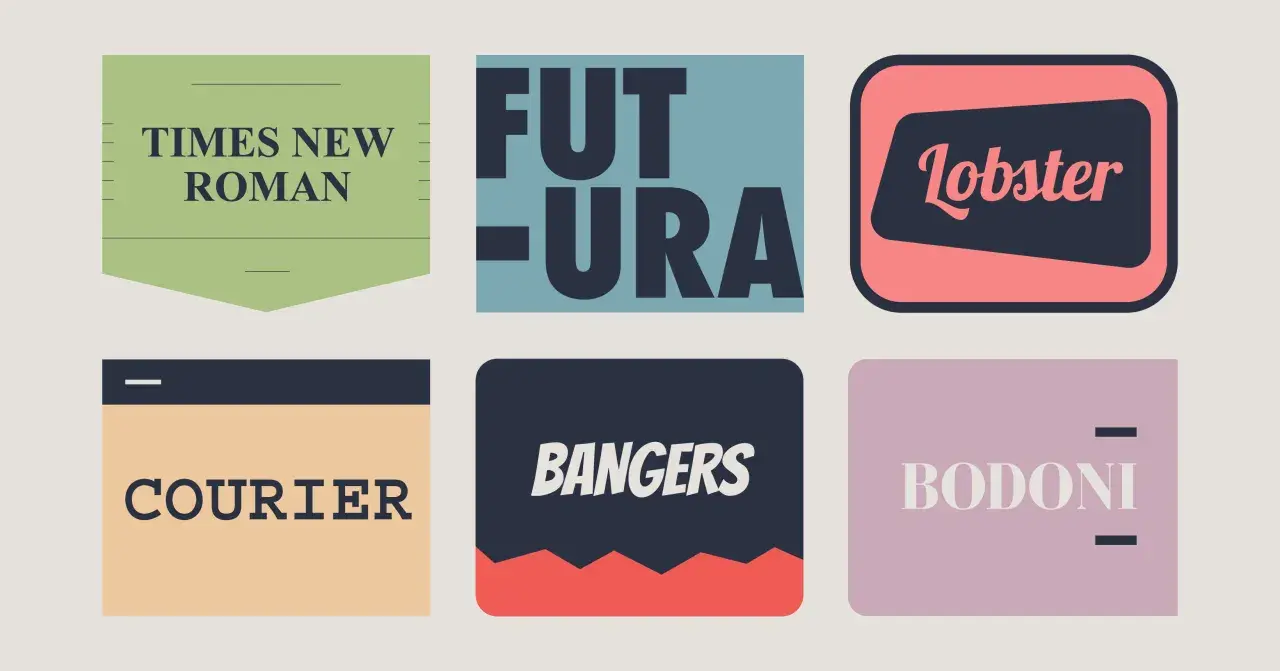
Dobór kroju pisma ma dziś większy wpływ na odbiór marki niż wielu właścicieli firm zakłada. Gdy analizuję popularne czcionki, patrzę nie tylko na modę, ale przede wszystkim na czytelność, charakter i to, czy dana rodzina rzeczywiście pomaga sprzedać usługę lub produkt. W tym tekście pokazuję, które kroje są najczęściej wybierane, dlaczego właśnie one wracają w projektach oraz jak dobrać font do strony, reklamy i materiałów lokalnego biznesu.
Najmocniejsze kroje to dziś te, które łączą czytelność z charakterem
- W interfejsach i na stronach nadal dominują proste sans-serify, bo są najłatwiejsze do czytania na ekranie.
- Inter, Roboto, Open Sans, Lato, Montserrat i Poppins to nazwiska, które wracają najczęściej, ale każdy z tych krojów ma inne zastosowanie.
- Serify znów zyskują znaczenie w markach premium, edytorialu i treściach eksperckich, bo dodają więcej powagi i ciepła.
- W praktyce lepiej wybrać 1 lub 2 rodziny pisma niż gonić za kolejną modną nazwą.
- Największą różnicę robi czytelność na telefonie, komplet znaków polskich i sensowna liczba wag.
- W marketingu lokalnym font ma wzmacniać komunikat, a nie go zagłuszać.
Dlaczego jedne kroje zyskują status standardu, a inne znikają z projektów
W typografii popularność rzadko bierze się z samej estetyki. Zwykle wygrywa krój, który dobrze działa w małym rozmiarze, ma szerokie wsparcie językowe, dostępny jest w wielu wagach i nie sprawia problemów w druku, na www oraz w aplikacjach. Właśnie dlatego neutralne sans-serify tak długo trzymają się na szczycie, a w 2026 roku coraz częściej widać też powrót do serifów w projektach, które chcą wyglądać bardziej dojrzale i mniej „generycznie”.
Ja patrzę na to bardzo praktycznie: font ma najpierw umożliwić szybkie odczytanie treści, dopiero potem budować nastrój. Jeśli krój jest efektowny, ale męczy wzrok albo traci jakość po zmniejszeniu, w realnym projekcie przegrywa z prostszym konkurentem. To dlatego w dalszej części skupię się najpierw na rodzinach najbardziej uniwersalnych, a dopiero potem na tych, które lepiej grają rolę akcentu niż głównego nośnika tekstu.
Najmocniejsza grupa sans-serifów do internetu i aplikacji
Jeśli miałbym wskazać segment, w którym najłatwiej znaleźć naprawdę bezpieczny wybór, byłaby to właśnie rodzina bezszeryfowa. To ona dominuje w UI, na stronach usługowych, w panelach, w e-commerce i w większości materiałów cyfrowych. Potocznie mówi się o „czcionkach”, ale projektowo lepiej myśleć o krojach pisma, bo to one decydują o rytmie tekstu, proporcjach liter i wrażeniu, jakie zostaje po kontakcie z marką.
| Krój | Charakter | Najlepsze zastosowanie | Co go wyróżnia | Na co uważać |
|---|---|---|---|---|
| Inter | Neutralny, nowoczesny, bardzo czytelny | UI, strony usługowe, body text | Świetnie działa na ekranie, ma uporządkowany rytm i daje wrażenie porządku | Bywa tak bezpieczny, że przy słabszym brandingu nie buduje żadnej osobowości |
| Roboto | Techniczny, stabilny, uniwersalny | Serwisy mobilne, aplikacje, treści informacyjne | Dobrze znosi małe rozmiary i nadal kojarzy się z funkcjonalnością | W brandingu może wyglądać zbyt „domyślnie” |
| Open Sans | Łagodny i neutralny | Dłuższe teksty, strony firmowe, blogi | To jeden z tych krojów, które nie przeszkadzają treści | Nie buduje mocnego wyróżnika, więc potrzebuje wsparcia innymi elementami identyfikacji |
| Lato | Przyjazny, lekko humanistyczny | Strony usług lokalnych, komunikacja B2C | Jest cieplejszy w odbiorze niż wiele surowych sansów | Przy zbyt wielu stylach w jednym projekcie traci lekkość |
| Montserrat | Geometriczny, wyrazisty, miejski | Nagłówki, logotypy, reklamy, plakaty | Daje mocny, nowoczesny akcent i dobrze pracuje w krótkim przekazie | W długich akapitach męczy bardziej niż kroje neutralne |
| Poppins | Równy, miękki, młodzieżowy | Landing page, social media, promocje | Ma przyjazny, współczesny charakter i dobrze wygląda w większych nagłówkach | Łatwo wyglądać nim zbyt podobnie do innych marek, które też wybrały go „bo jest modny” |
| Manrope | Minimalny, świeży, lekko premium | Nowoczesne usługi, software, marki osobiste | Jest bardziej charakterystyczny niż typowy neutralny sans, ale nadal nie przeszkadza treści | W projekcie bez odpowiedniego kontrastu może wydać się zbyt cienki |
| Source Sans 3 | Spokojny, redakcyjny, uporządkowany | Serwisy contentowe, dokumentacja, dłuższe treści | Świetnie znosi długie czytanie i dobrze łączy się z serifami | Nie robi efektu „wow”, więc trzeba go świadomie zestawić z resztą identyfikacji |
Jeżeli projekt ma być bezpieczny, najczęściej wystarcza jeden krój do tekstu i jeden do nagłówków. W praktyce to właśnie Inter, Open Sans, Roboto albo Source Sans 3 robią największą robotę, bo nie walczą z treścią. Gdy interfejs jest już uporządkowany, naturalnym krokiem staje się pytanie, czy marka nie skorzysta na bardziej eleganckim serifie.
Serify wracają tam, gdzie marka chce brzmieć dojrzalej
- Source Sans 3 + Source Serif 4 - zestaw bardzo praktyczny, szczególnie tam, gdzie tekstu jest dużo i musi pozostać wygodny w czytaniu.
Jeżeli mam dać jedną radę na koniec, brzmi ona prosto: nie wybieraj fontu wyłącznie dlatego, że jest modny. Najpierw sprawdź, czy pomaga czytać, potem czy pasuje do tonu marki, a dopiero na końcu czy wygląda efektownie w mockupie. W typografii najczęściej wygrywa nie najbardziej widowiskowy wybór, tylko ten, który po cichu robi swoją robotę przez cały projekt.